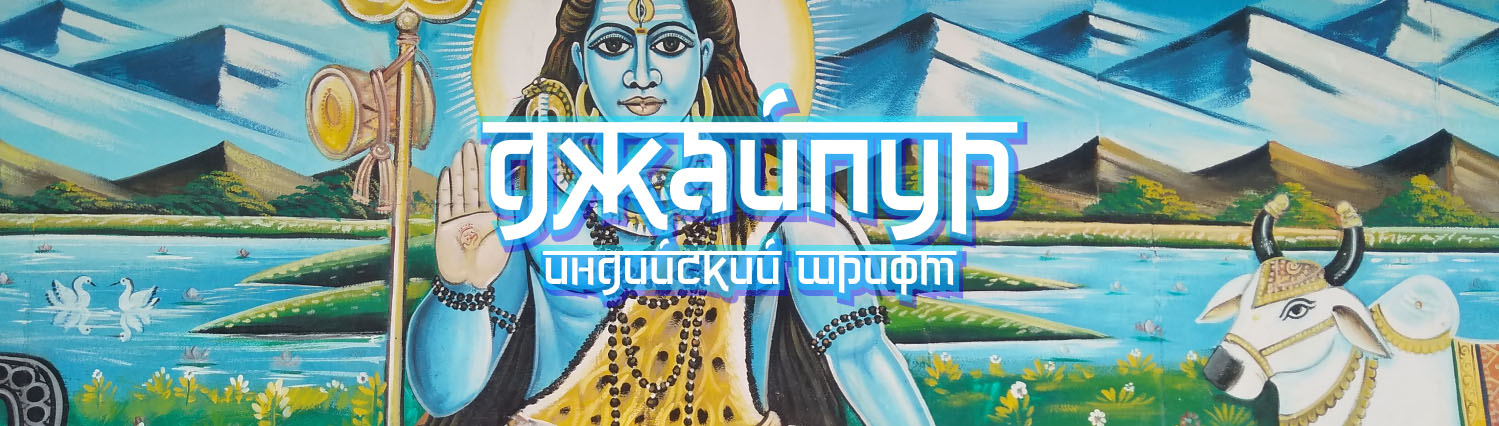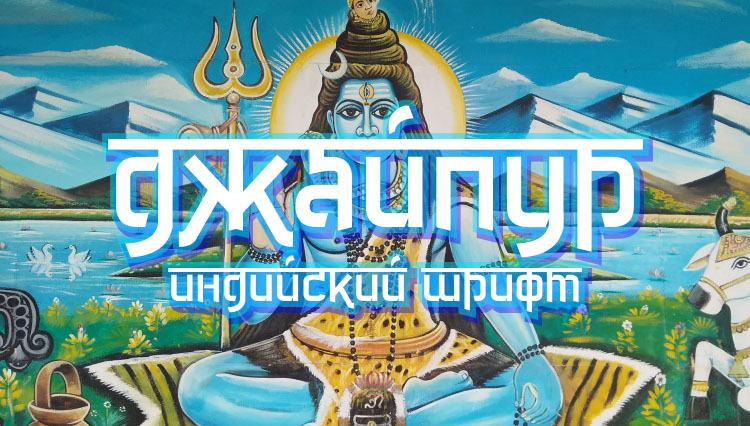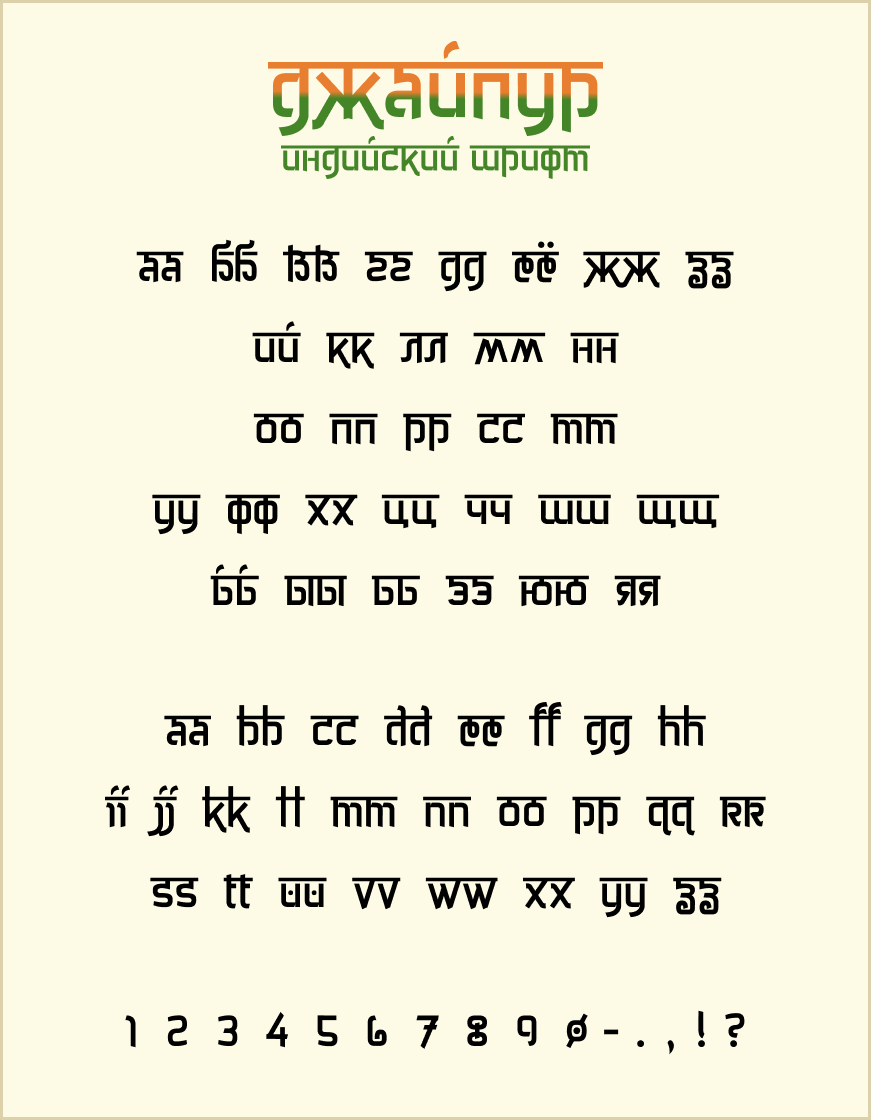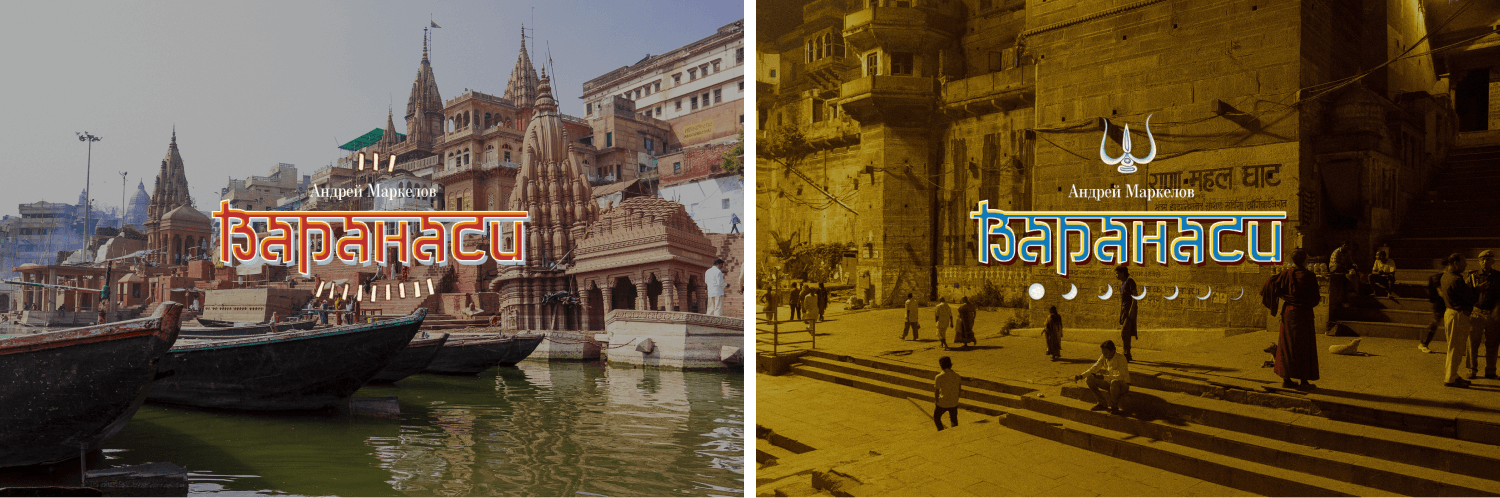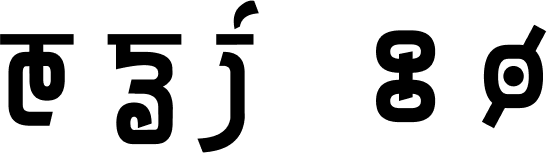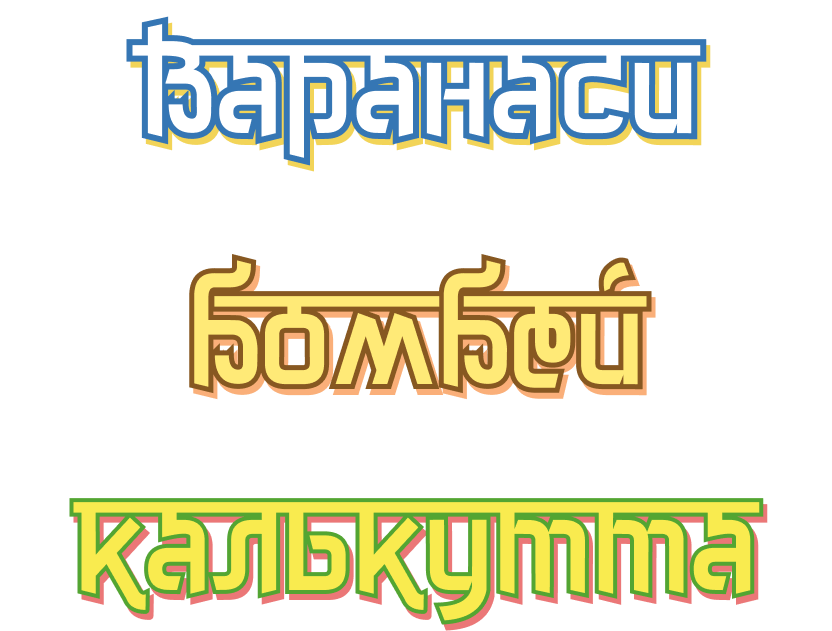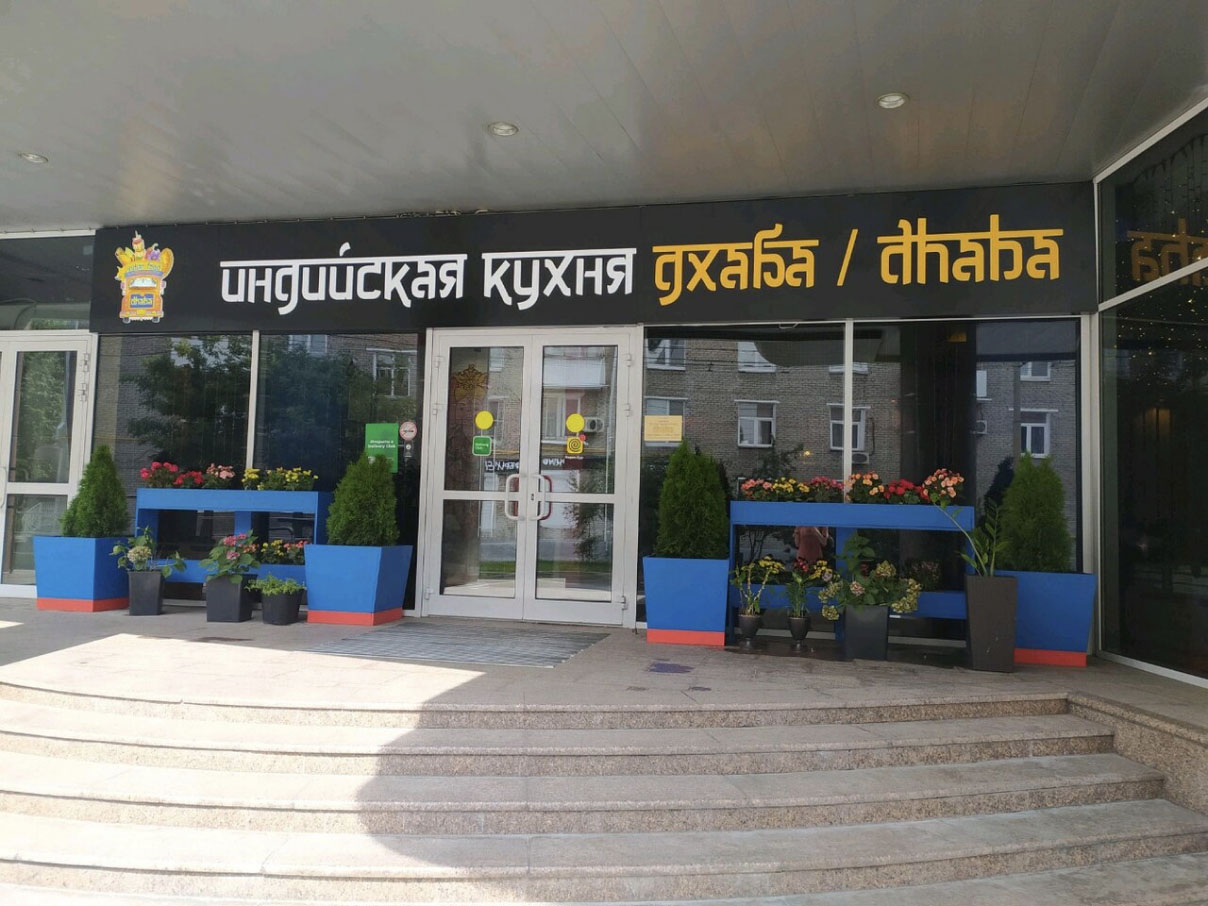
Шрифт в индийском стиле Джайпур
Джайпур — русская, кириллическая версия шрифта Jaipur, стилизованного под индийскую азбуку деванагари.
В шрифте нет символов номера, скобок, арифметических знаков и прочих, но есть основные знаки препинания, поэтому используйте Джайпур только для набора заголовков и логотипов на русском языке.
На русском языке существует крайне мало шрифтов, выполненных в индийском стиле. В большинстве случаев используется чудовищный шрифт DS Izmir.
Измир имитирует деванагари из рук вон плохо и совершенно не похож на то, как пишут в Индии современные таблички и рекламные постеры на стенах.
Хороших шрифтов в стиле деванагари мало и на латинице. Один из них — Jaipur от Vic Fieger. Теперь этот шрифт переведен на русский язык и доступен для свободного использования.
Шрифтом Джайпур написаны все заголовки в рассказах про Индию.
В латинской версии наиболее красивы и своеобразны буквы «е», «z», «j» и цифры «8», «0».
Кириллическая версия обладает правильными строчными буквами «м» и «т», сложной и замысловатой буквой «б», стильными «ж» и «я».
Джайпуром лучше всего писать так, как делают это в Индии на самодельных рекламных указателях: вырвиглазные цвета, тени, обводка букв.
Должно получаться вот так:
Примеры использования
Пока мне известен только один пример использования шрифта в жизни — это вывеска ресторана “Дхаба” на м. Белорусской. Смотрится отлично.